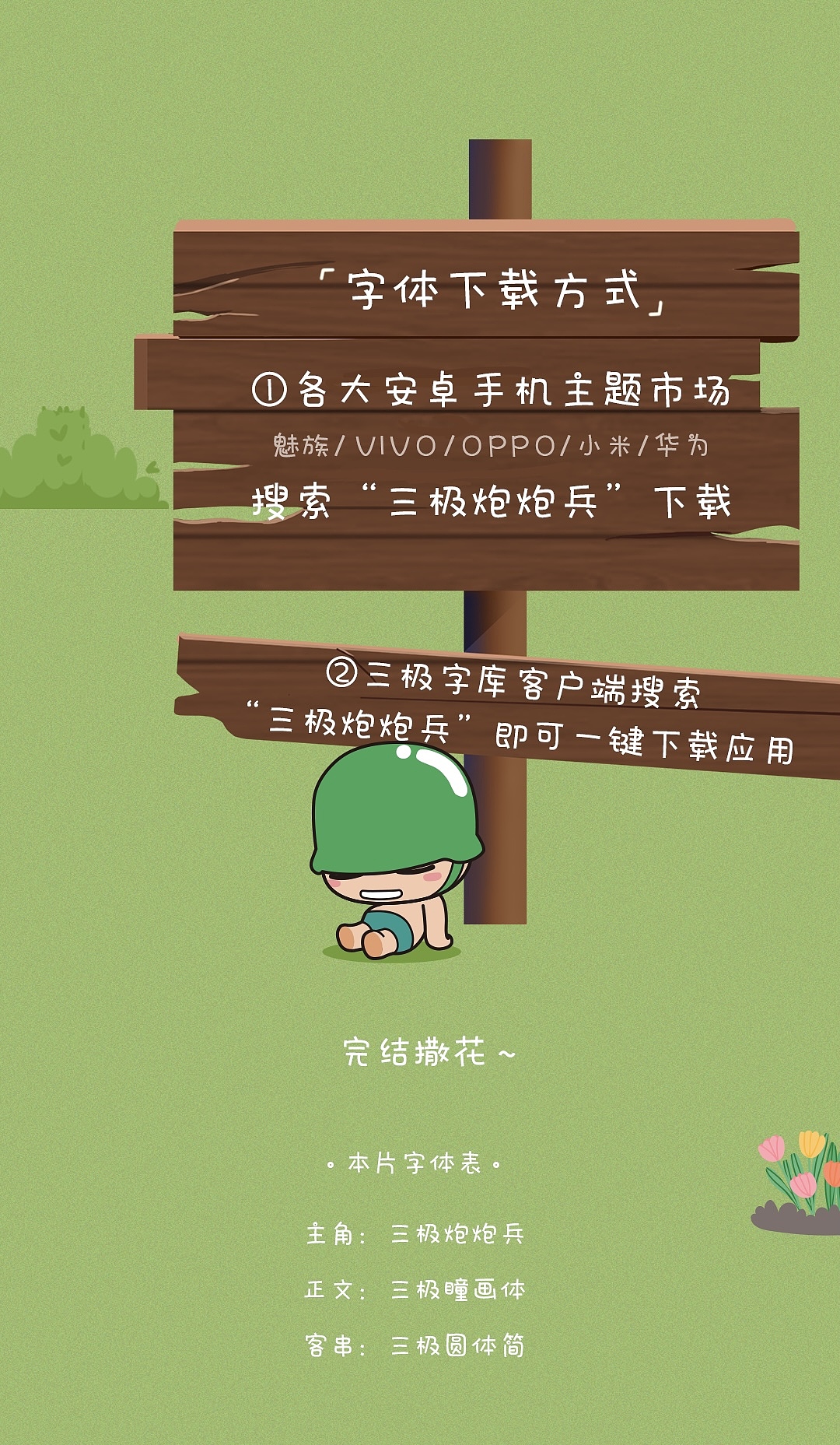
三极字库x炮炮兵联名字体 | “三极炮炮兵”报到 !
三极炮炮兵,借手写体风格表现出炮炮兵这一ip鬼马俏皮的屏幕形象。字形上,字体结构灵动不呆板,笔画造型上,所有笔画都采用弧线,整体圆润可爱。笔画造型还参考了炮管的外形,笔画两端粗细不同更加凸显了字体的动感。在一些封闭笔画处做了断笔设计,字体亲切兼具呼吸感,在保证显眼的同时让字体笔画不会粘连。它是炮炮兵品牌形象的进一步发展,有助于品牌对外输出时树立统一、和谐、高识别度的视觉形象。